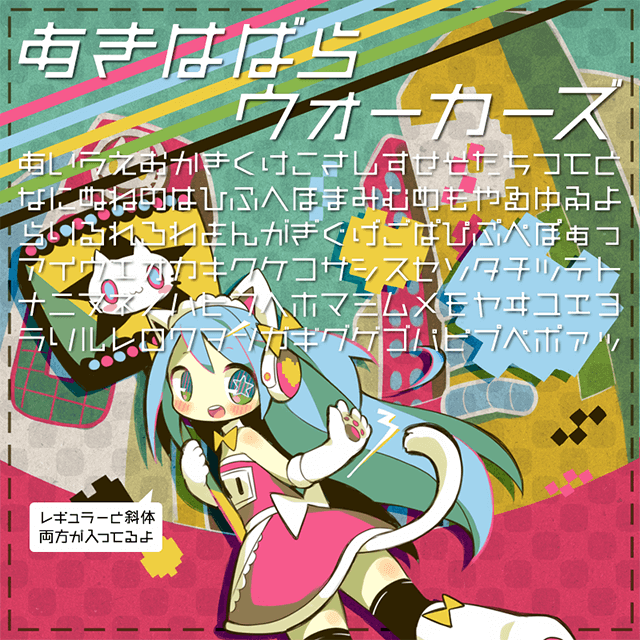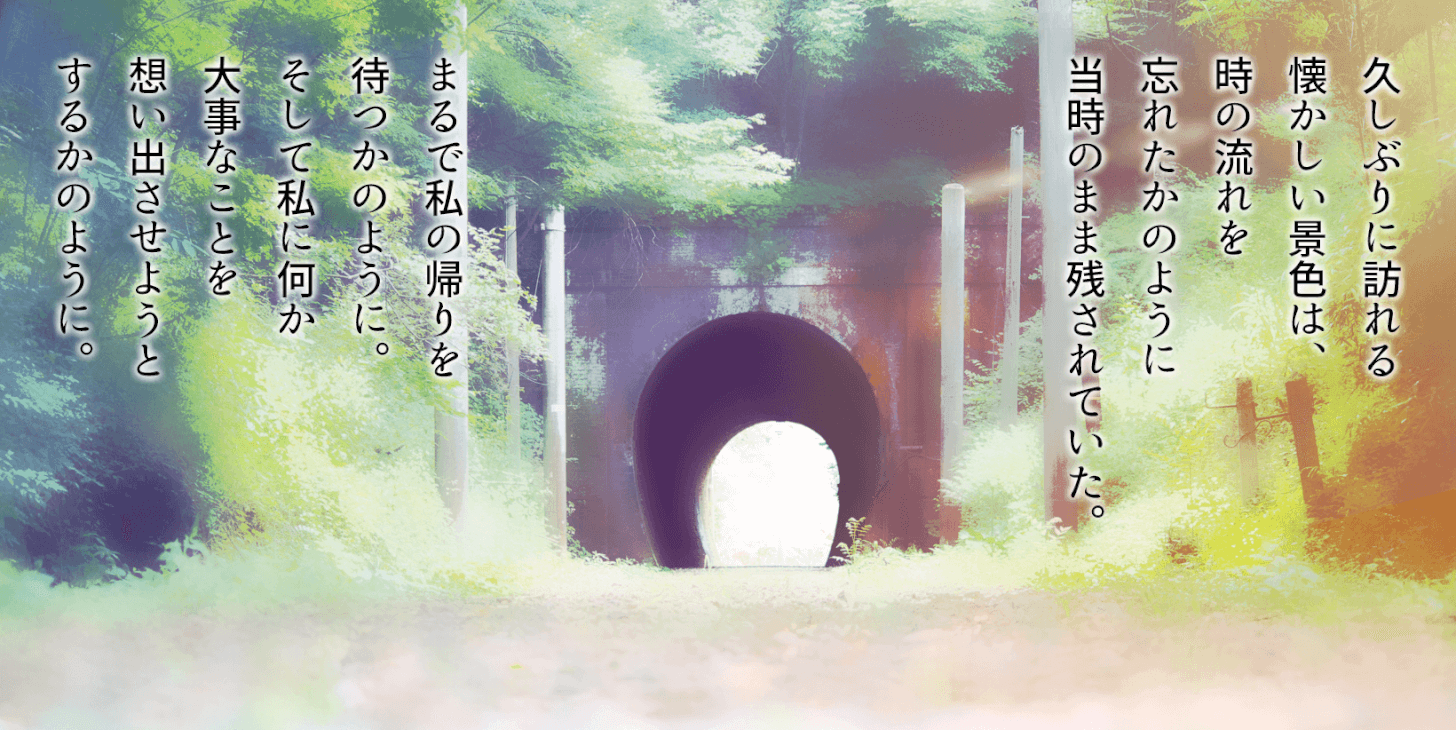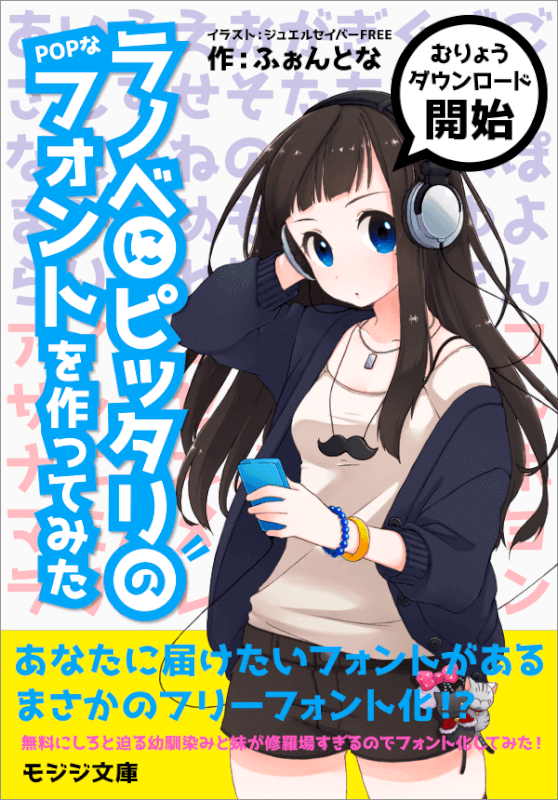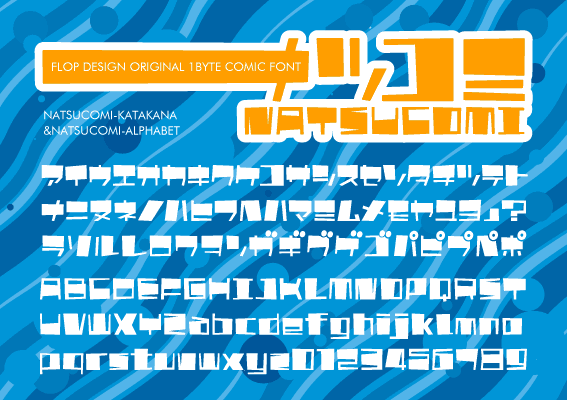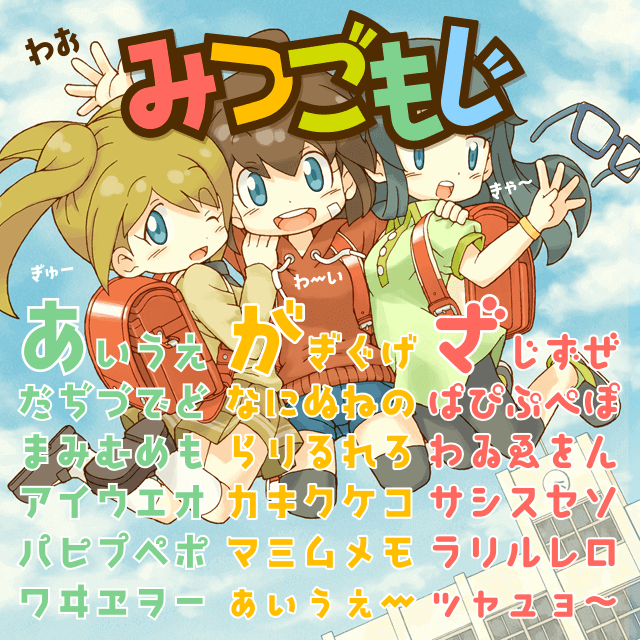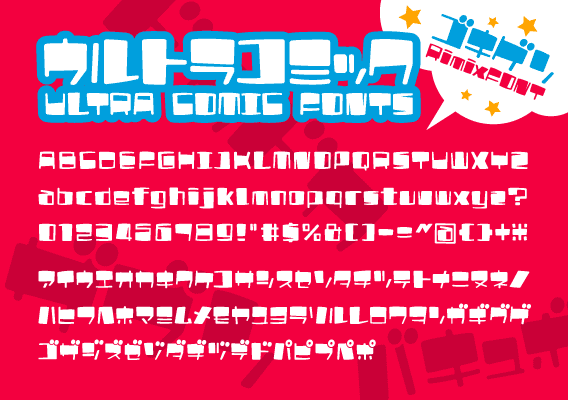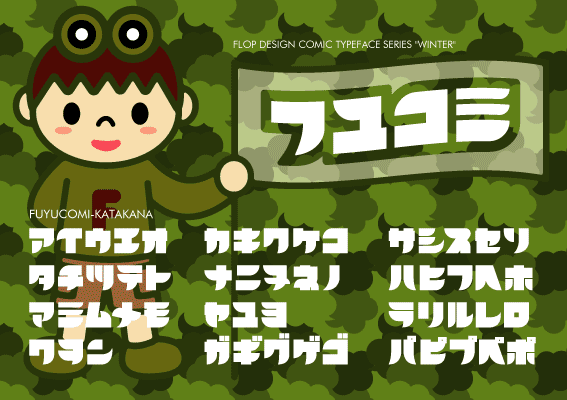
漫画や同人誌で使える漫画フォント27選
文字を入力するだけで簡単にコミックや同人誌で使われそうな文字を表現できるフォントを27つ集めました。漫画の読みやすさのためにもフォント選びは大事です。
今回、ご紹介するフォントの中から自分の漫画や同人誌に合うフォントを見つけてみてください。
FUKIDASHI
文字を入力する感覚で漫画のセリフなどに使える吹き出しを表現できるフォント。
g_太手書き丸
フェルトペン等のマーカーで丁寧に描き文字したようなフォント。丸っこい、かわいい、popな感じになっています。
GL-アンチック
アンチック体かな文字フォント。ひらがな・カタカナ・記号等のみです。
GL-アンチックPlus
上記でご紹介したGL-アンチック に M+ フォントを合成したアンチゴチ体の試験公開版。
Kokecco2-KT
マンガの擬音ぽく奥行きを多少付けた特徴的なカタカナフォント。
あきはばらウォーカーズ
今時の秋葉原をイメージして作ったフォント。細身でスタイリッシュですが、どことなくかわいらしさというかユーモラスな雰囲気漂う感じのフォントです。
あははもじもじ
擬音語・擬態語にぴったりのユニークな手書き風フォント。
ウルトラコミックフォント
極太なポップな感じのゴシック体。
オレのカノジョがイタすぎる
漫画やラノベのようなコミカルさとハネるような勢いが特徴のかなフォント。
けいふぉんと!
『けいおん!』のロゴタイプをヒントにしたフォント。太めのフォントなので、本文よりは見出し・タイトルなどに向いています。
ジョジョフォント
漫画やアニメの「ジョジョの奇妙な冒険」に出てくる特徴的な擬音(オノマトペ)が再現できるフォント。
ナツコミフォント
文字の一部が極太でコミカルなデザインされたフォント。
はらませにゃんこ
柔らかさと雑さが魅力のロゴ向けのフォント。
ファットボーイウルトラ
とにかく太いフォント!太くてインパクトあるアルファベットを使いたいという方にピッタリ。
フユコミフォント
全体的に太めでシャープなラインが特徴的なフォント。
みつごもじ
3種類のフォントがセットになったポップなタイトル向けのフォント。
やさしさアンチック
ゴシック体の漢字にあわせた太い明朝体の「かな」が組み合わされたフォント。普通のアンチック体よりも太さの差が少ないので漢字との統一感が高い漫画用フォントにオススメです。
ラノベPOP
軽やかで弾むような、楽しい雰囲気のキュートなPOP体フォント。